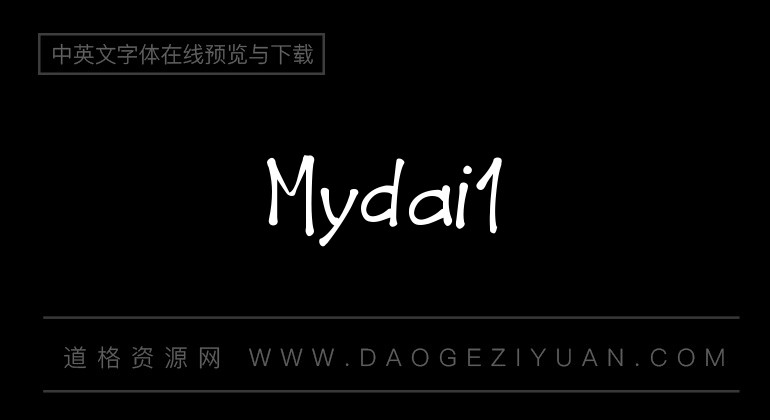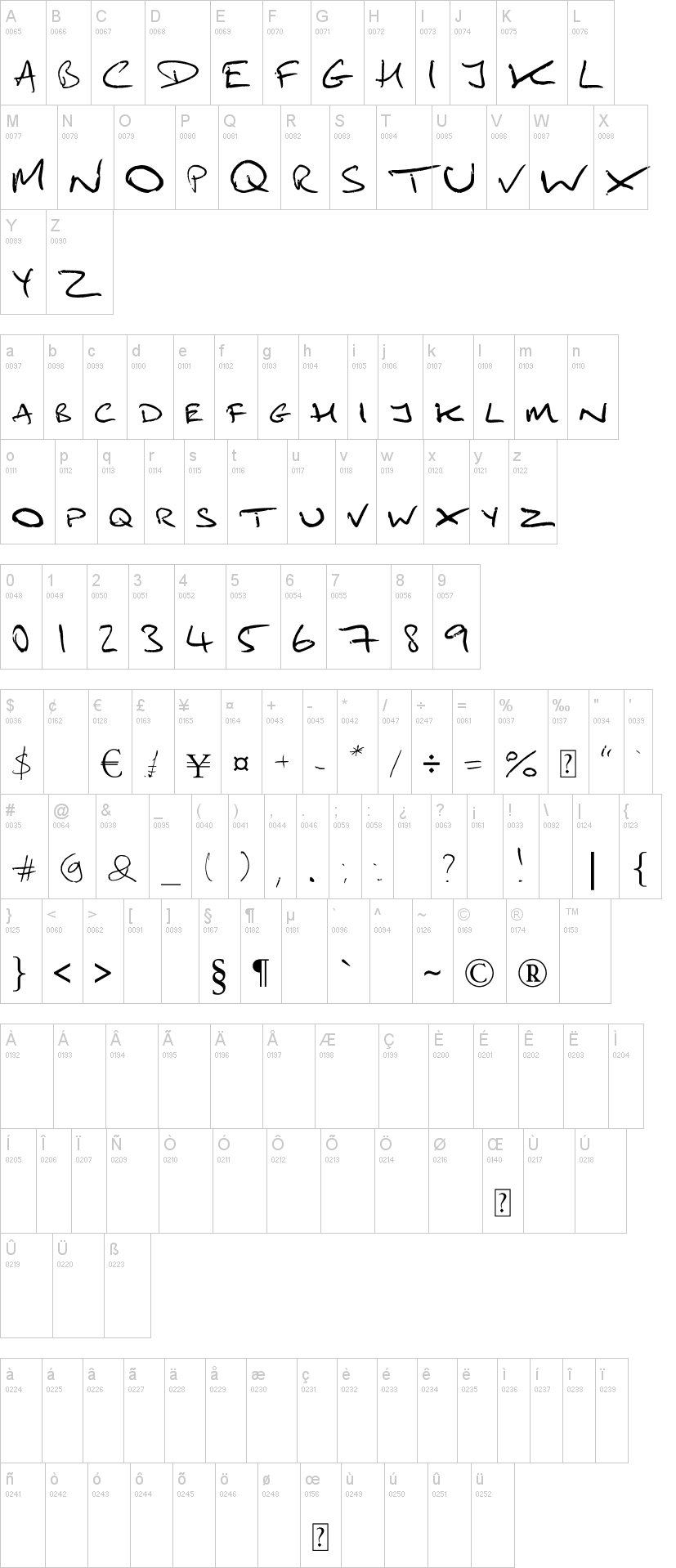
Mydai1
Mydai1 字体是一款简洁、优雅的中文字体,它由深圳市美大设计研究院设计研发,由深圳市美大设计研究院和深圳市美大技术有限公司联合推出。Mydai1字体有着超强的识别率和辨识度,可以清晰的表达文字的细节,是一款极具视觉冲击力的字体。Mydai1字体拥有全面的英文字体,可以满足不同的设计需求。
Mydai1是一款非常不错的手写艺术字体,具有很好的视觉感,适合于文化类的宣传设计、商业类品牌的广告和产品包装设计以及个性化文字排版等较多场景。